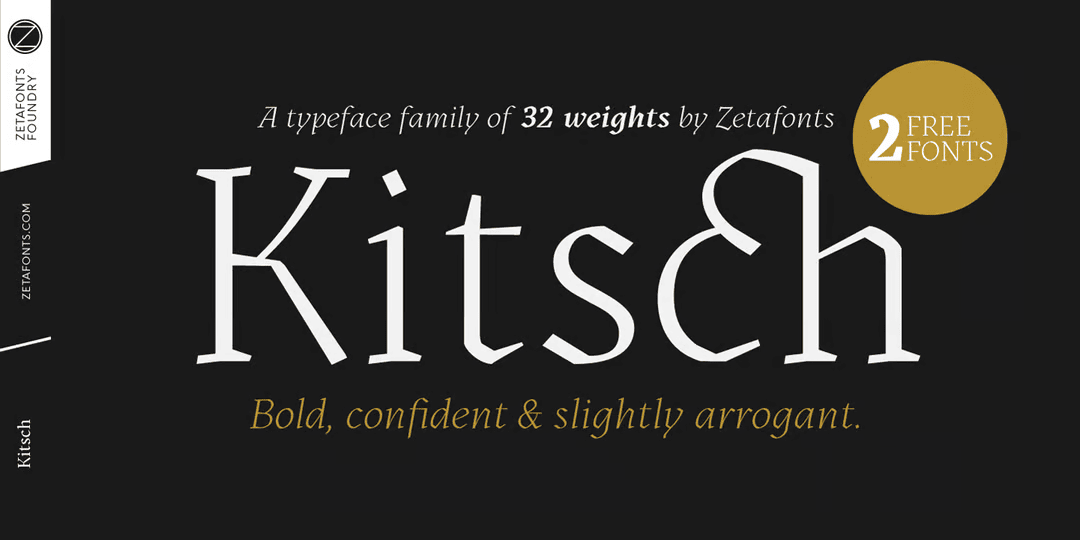
Kitsch
とにかくストロークがカクカクしている変わったオールドスタイルローマン。どうもカリグラフィーで使用する幅広のブロードニブを用いてデザインしたそうで、書体のロタンダ Rotunda やバスタルダ Bastarda を参考にしたとあるが、どの辺がそうなのかよく分からん(笑)。とにかくカーブのアウトラインが唐突にカクっと折れていてユニークだが、骨格は割とスタンダードなので、小さく使うと普通のオールドスタイルに見えたりもする。オプティカルになっており、本文用の Text と見出し用の Display があって、それぞれにイタリックもあって8ウェイト。なので長文も想定されて設計されている。グリフも豊富でギリシャ文字やキリル文字もサポート。